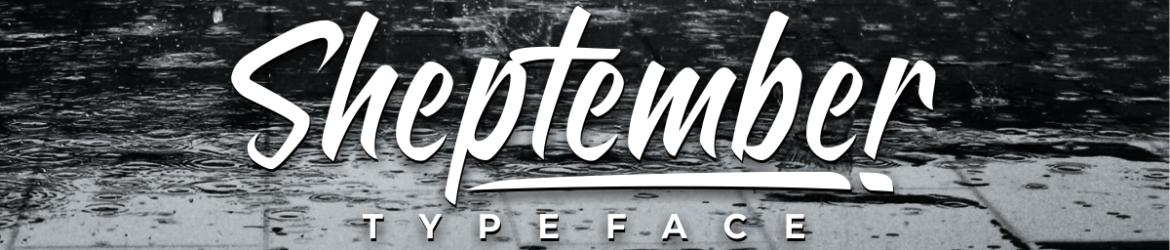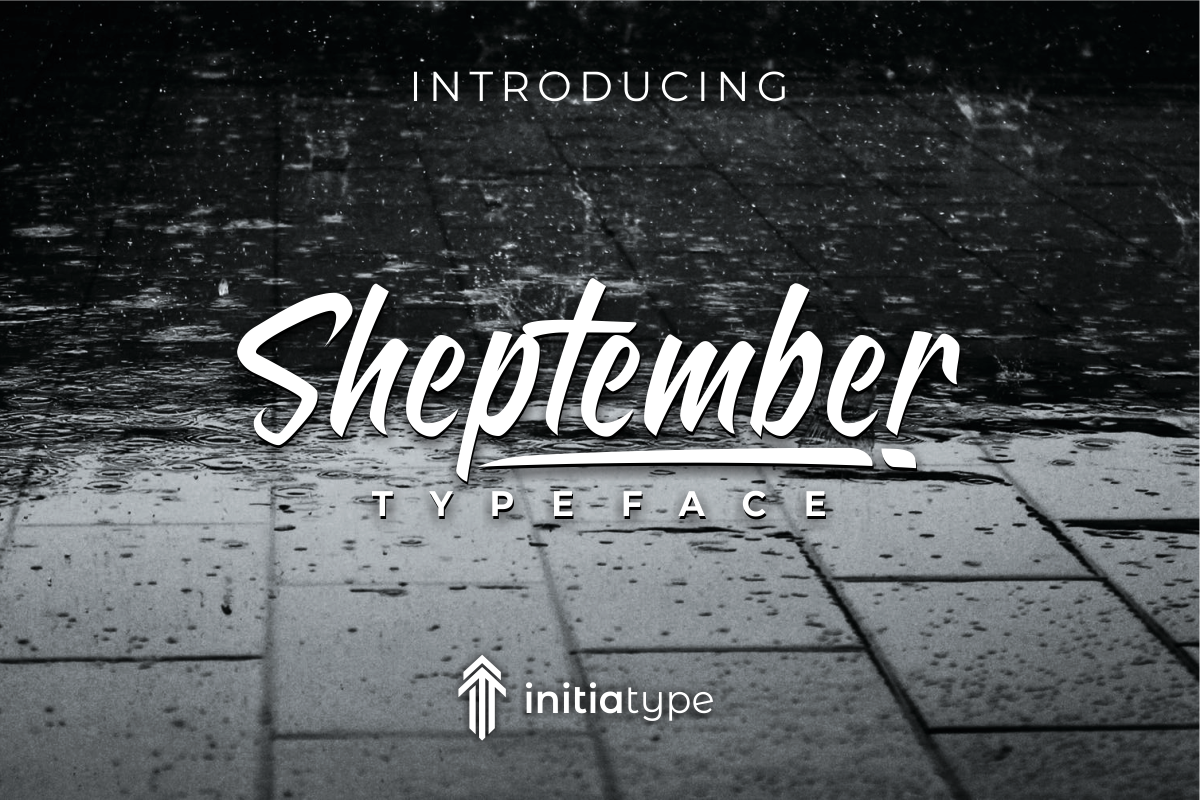
Sheptember Script Font
Introduzimos a Sheptember Font! Desenhada pelo Francesco Canovaro e compartilhada pela InitiaType, é uma fonte simples e elegante, equipada com ligaturas. Esta fonte exibe elegância, sofisticação, leitura fácil, estilo e atratividade natural. Perfeita para aplicações variadas como marca d’água em fotografias, assinatura ou logo de assinatura, citações, capa de álbum, cartões de visitas e projetos gráficos de negócios de qualquer natureza. A Sheptember Font é a escolha perfeita para dar um toque especial aos seus trabalhos, elevando-os ao nível mais alto. Seja para criação de marca d’água em fotos ou desenhos de assinatura, essa fonte atinge o máximo da sua beleza e funcionalidade. Perfeitamente adaptável a uma variedade de projetos, desde cartões de visita até capas de álbum, garante um toque único que torna seus trabalhos um destaque no meio dos outros.